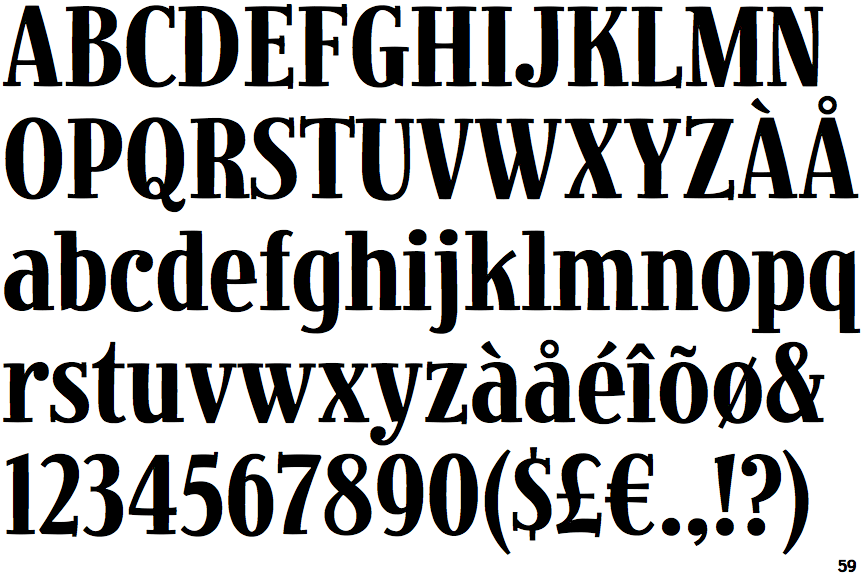
Bräuchte mal wieder einen Rat...
ich bräuchte mal wieder das geschulte Auge eines Fachmannes (oder einer Fachfrau ^^). Es geht um diese Seite:
es geht dabei um den Schriftzug unter dem Logo "DAS NATIONALPARKHOTEL".  Ich habe zwar die eine oder andere Schrift gefunden, die (für mich) dieser recht ähnlich ist, aber meistens haperte es am "S".
Hat jemand eine Idee, welcher Font das sein könnte?
Er meint den Schriftzug "HOTES FRIEDRICHS".
Hmm, ich denke, das ist adaptiert und die University könnte Pate gestanden haben.
Das würde ich aber eher ausschließen. Das gibt es einige Ansätze zum suchen: Bernhard Modern ... Chesterfield ... Belwe ...
Dann kommt man auch sehr schnell auf die Jimbo ...
Typeface: Jimbo Condensed
Designer: Jim Parkinson
Year: 1995
Irgendwo aus der Ecke ... Und ich habe schon sehr ähnliche Schriften gesehen ... Damit meine ich aber nicht so was:
Wobei diese Schrift möglicherweise doch einen Einfluss gehabt haben könnte? Was liest der/die Friedrich den so?